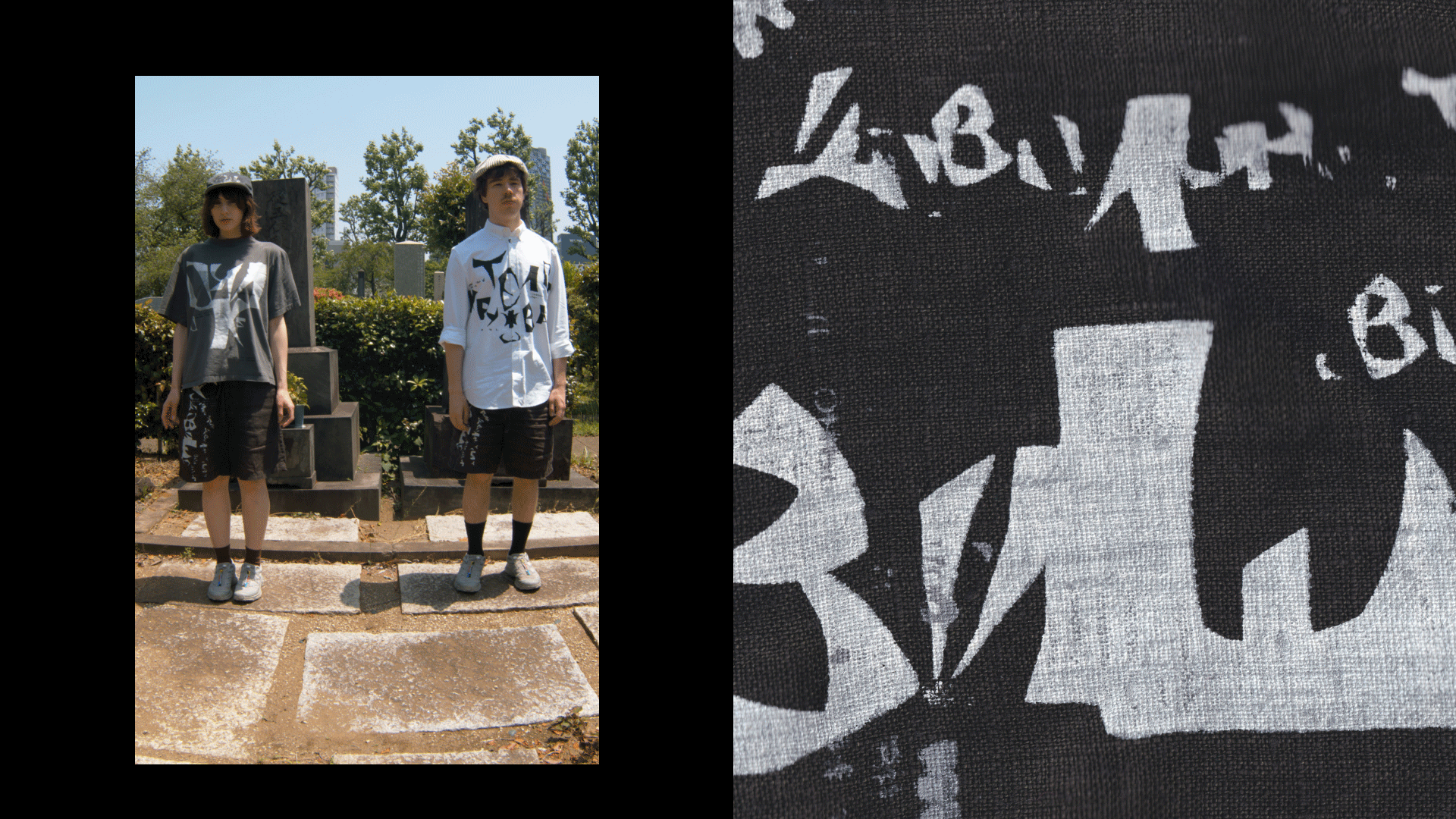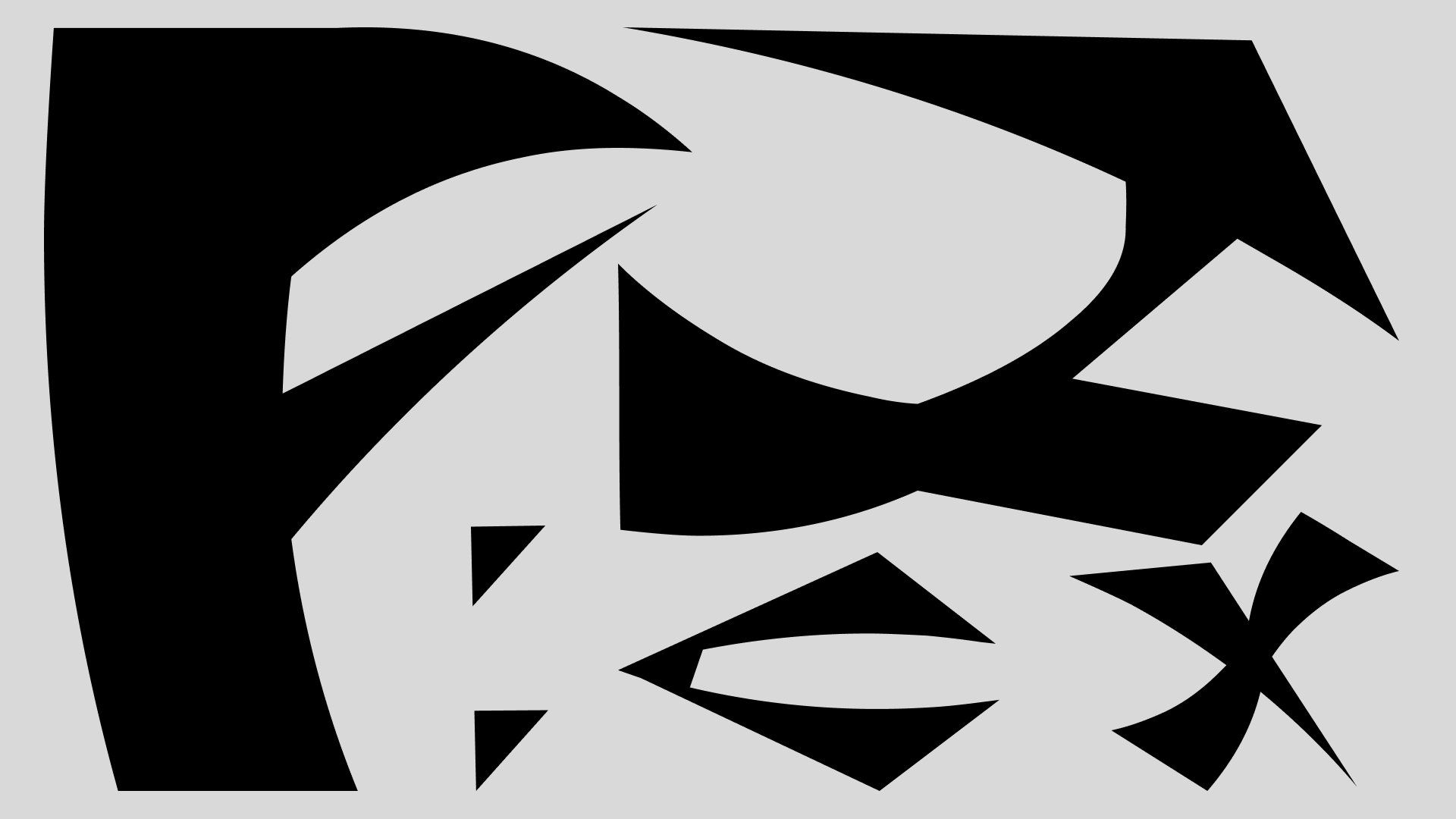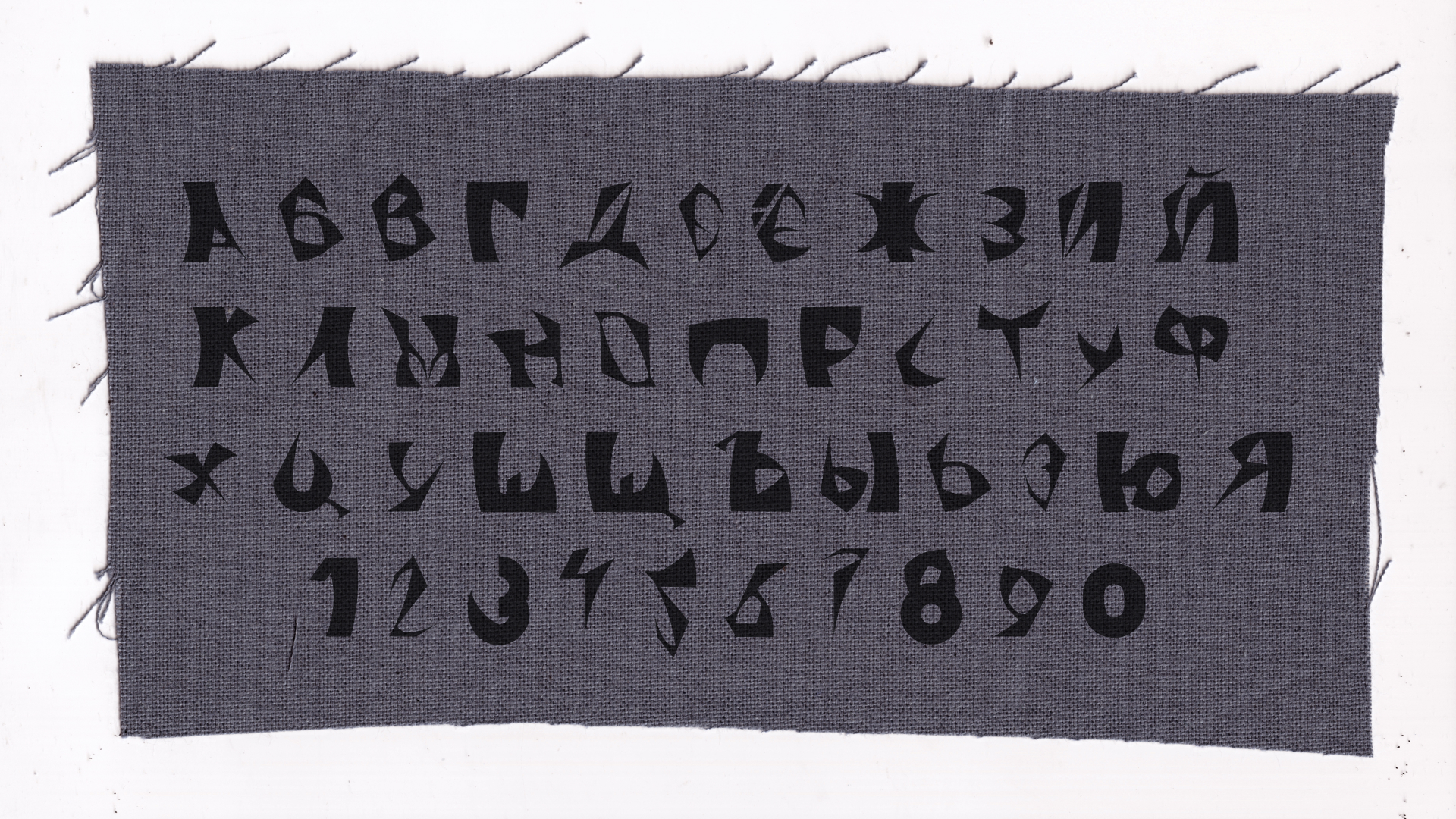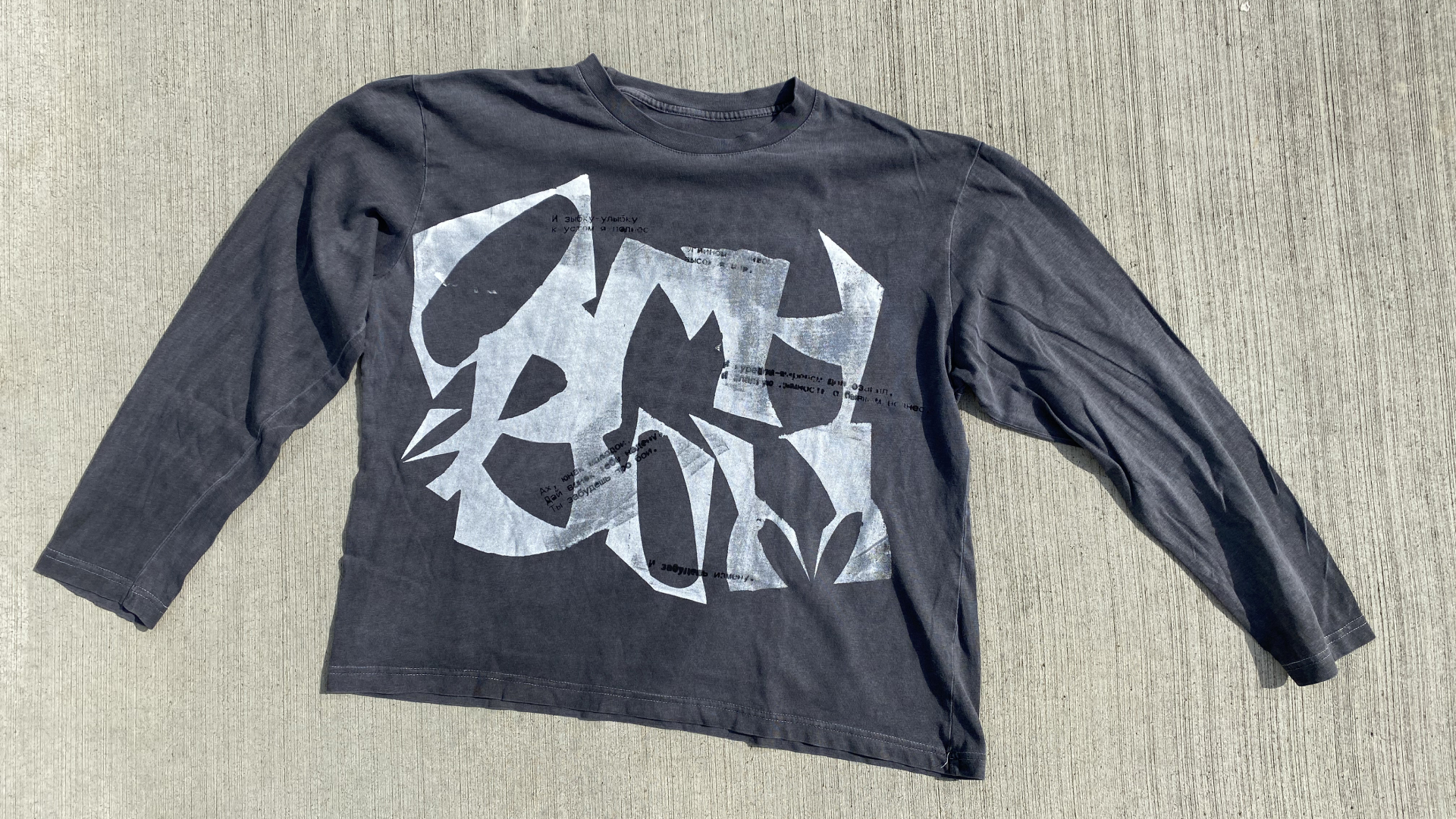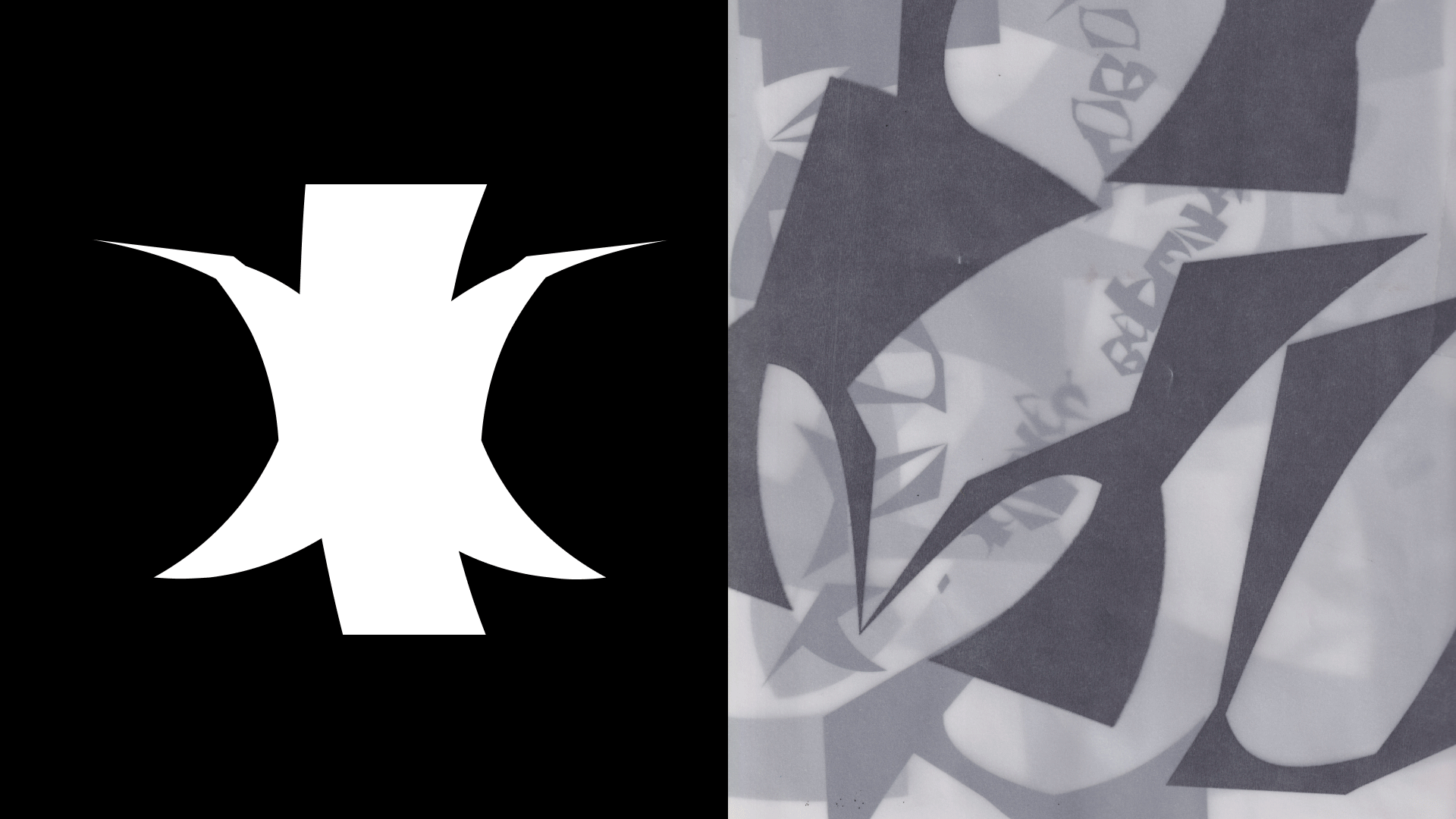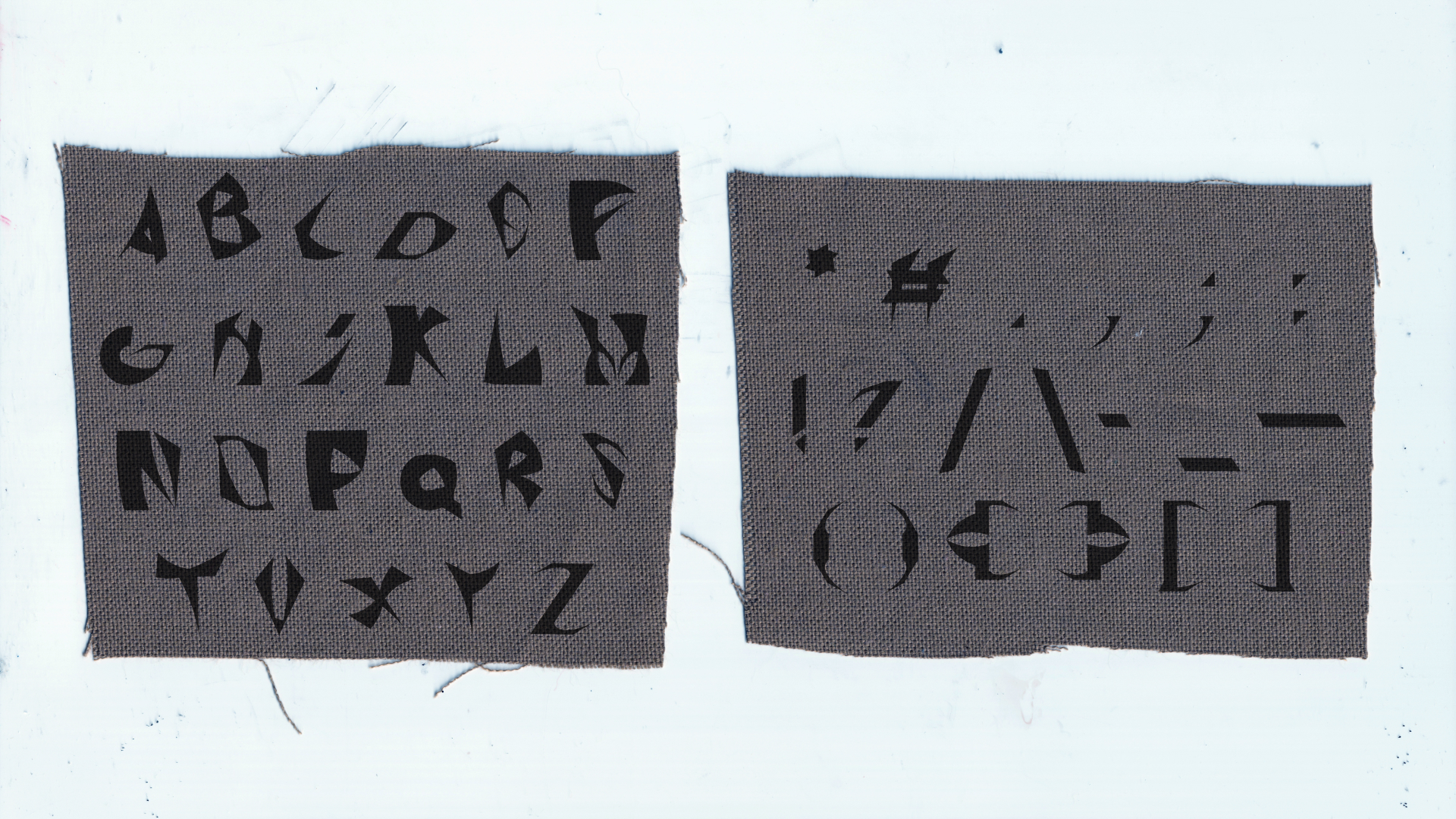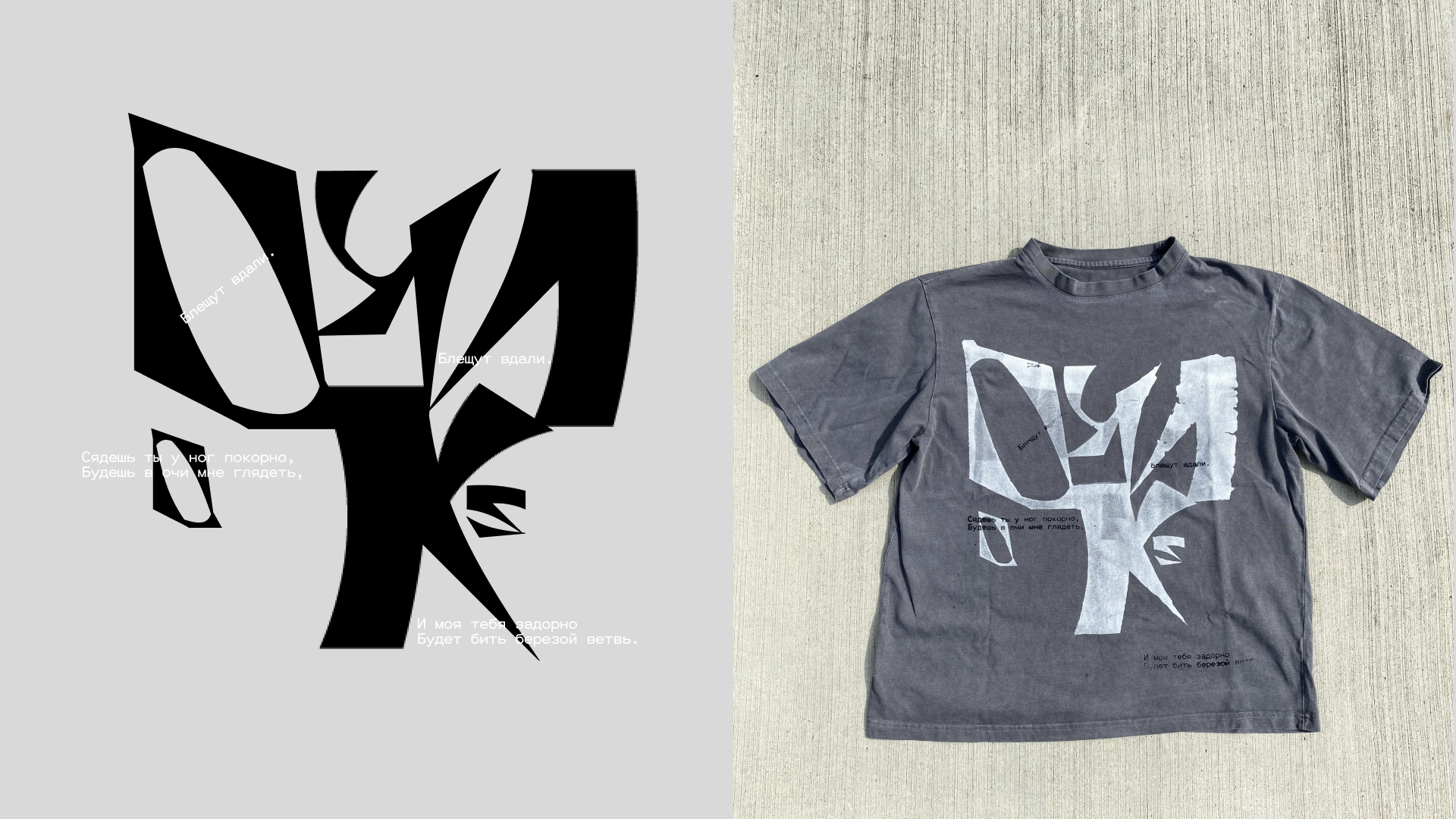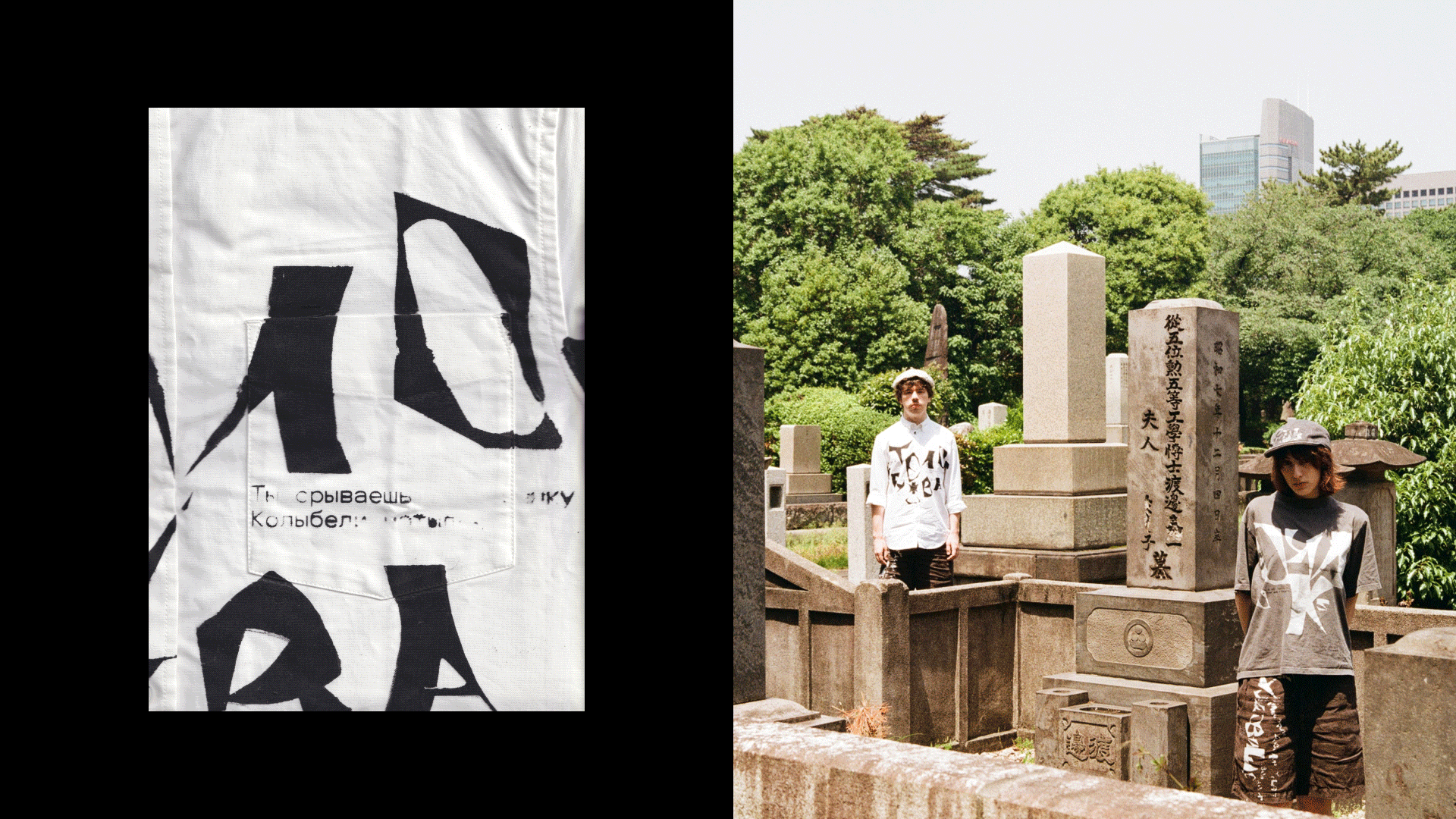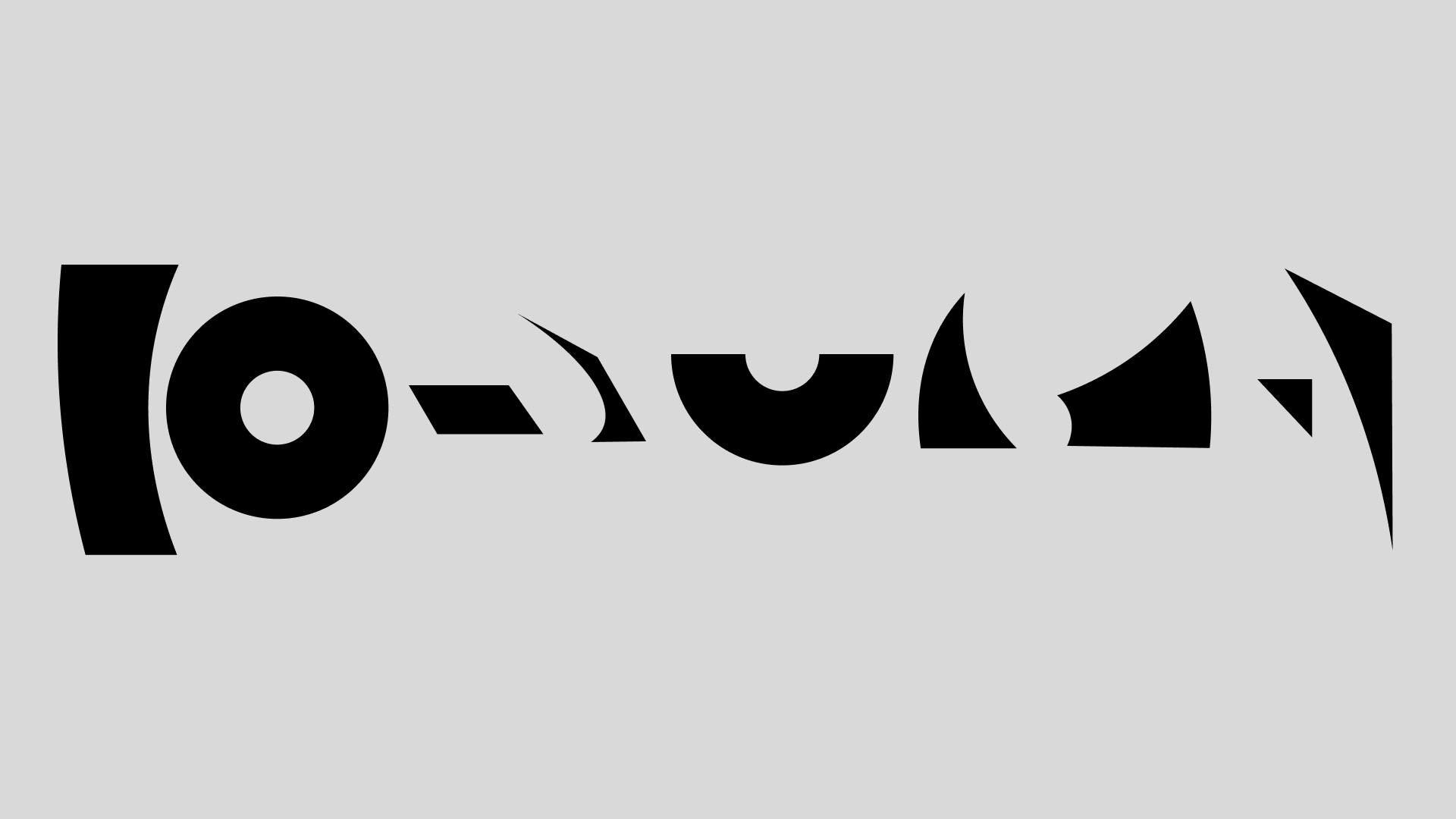
Экспериментальный шрифт
Velimir
шрифт, создан на основе выкроек и порванной ткани которая остаётся после производства одежды.
коллекция одежды включает в себя базовые вещи, акцентируя внимание на принтах — тексте. в основе принтов — стихи Велимира Хлебникова, где ключевым элементом выступает шрифт. таким образом, принт сочетает в себе не только выразительный силуэт букв,
но и глубокие идеи великого поэта.